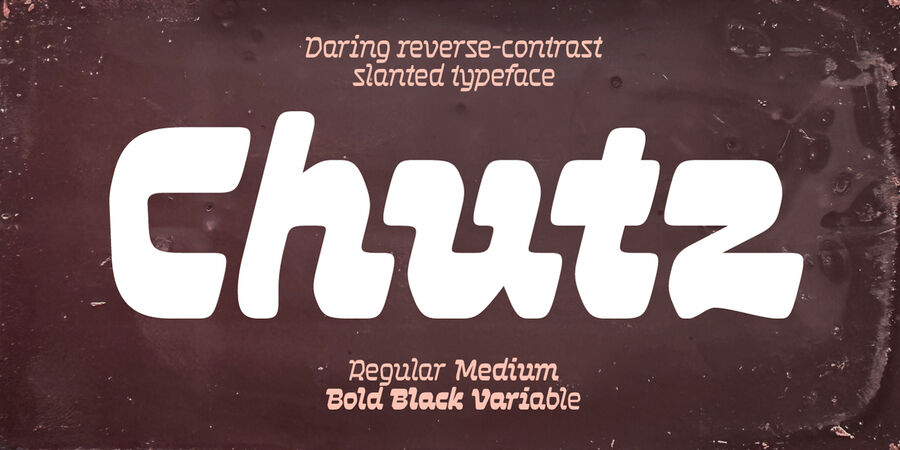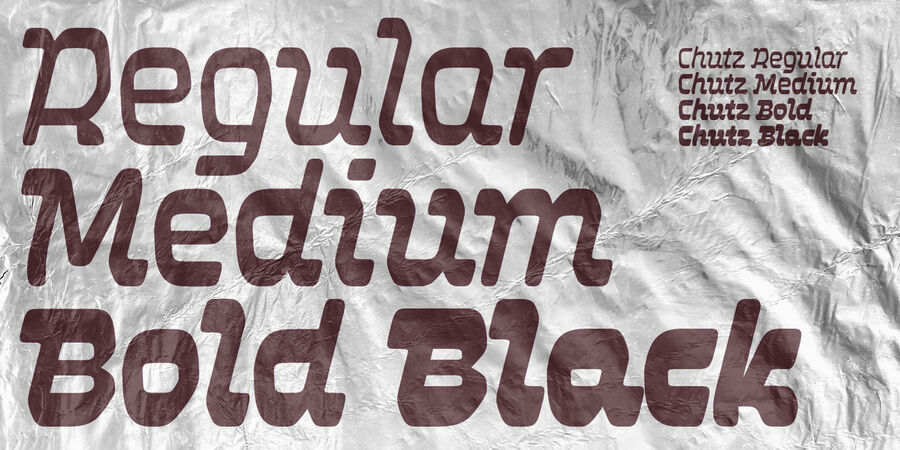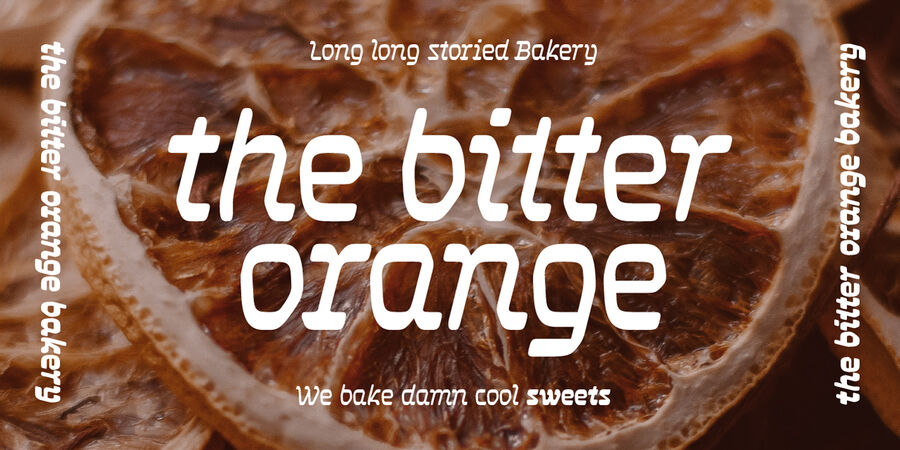
Опис гарнітури ChutzChutz це зухвала шрифтова гарнітура з нахилом, зворотним контрастом та горизонтально спрямованими штрихами, розроблена для єврейського бренду Chutzpah компанії Feisty Foods розташованої в Брукліні, Нью-Йорк. Шрифт має три мети – відчуватись єврейським, смачним, та зухвалим. Для передачі характеру івриту в латинській, грецькій та кириличній писемності застосовані такі засоби як реверсний контраст (протилежний латинському) де горизонтальні штрихи товщі за вертикальні, та горизонтально спрямовані каліграфічні штрихи притаманні івритській писемності і які роблять літери більш квадратними.
Щоб виглядати смачно та відчуватись як тісто (у стилях Bold і Black) дизайн отримав м'які заокруглені деталі та насичений типографічний колір. Для передачі сміливості та зухвалості структура літер отримала нахил різного куту для різних літер. Наприклад більшість літер мають латинський нахил (направо), а деякі інші літери як то CGOQabcdegopqy мають притаманний івриту нахил (наліво). Таке поєднання різних кутів нахилу надає шрифту зухвалий комплексний характер готовий до сміливих дій. Стилі: Regular, Medium, Bold, Black, Variable Font. У промо зображеннях використані фото Ольги Рафайлик, та фото Marta Dzedyshko, Josh Sorenson з Pexels. Шрифт розробив Михайло Рафайлик у 2023 році та значно розширені та оновлені у 2024. Chutz підтримує 111 мовУкраїнська, Англійська, Німецька, Польська, Португальська, Іспанська, Грузинська, Казахська, Іврит, Французька, Грецька (сучасна), Арабська, В'єтнамська, Російська, Чеська, Голландська, Італійська, Шведська, Турецька, Фінська, Білоруська, Грецька, Татарська, Сербська, Болгарська, Естонська, Литовська, Албанська, Африкаанс, Баскська, Бретонська, Валенсаска, Galician, Гельська (Шотландська), Данська, Індонезійська, Ірландська, Ісландська (Win), Каракалпацька, Каталонська, Норвезька, Окситанська, Ретороманська, Самі Лулі, Тсванська, Узбецька (Лат.), Фарерська, фризька, Чаморро, Естонська (Win), Південносаамська, Албанська (Win), Угорська, Верхньолужицька, Карельська, Латвійська (Mac), Литовська (Mac), Маорійські (Mac), Молдавська (Лат.), Нижньолужицька, Румунська (Win), Словацька, Словенська, Туркменська (Лат.), Хорватська (Win), Естонська (Mac), Курдська, Латишська, Маорійські, Руминська, Абазинська, Аварська, Агульська, Адигейська, Даргинську, Інгуську, Кабардино-Черкеська, Кабардинська, Карачаєво-Балкарська, Кумицька, Лакська, Лезгинська, Македонську, Мордовсько-Мокшанська, Мордовсько-Ерзянська, Ногайська, Рутульська, Табасаранська, Татська, Цахурська, Чеченська, Азербайджанська (Кир.), Башкирська, Бурятська, Дунганска, Коломацька, Киргизька, Монгольська (Кир.), Таджицька, Талиська, Тувинська, Туркменська (Кир.), Узбецька (Кир.), Уйгурська, Ідиш, Татська (Єврейська), Дарі, Малайська, Перська (Фарсі), Пуштунська, Урду Функції сімейства шрифтів ChutzЗастосування гарнітури у верстці:
Асоціації з сімейством шрифтів ChutzОсобистість і характер гарнітури:
М'який, доброзичливий, добрий, оптимістичний, літній, смачний, здоровий, свіжий, оригінальний, самобутній, цікавий, пластичний, гнучкий, гладенький, якісний, грайливий, динамічний, теплий, святковий, апетитний, емоційний, яскравий, спекотний, кольоровий, експериментальний, тусовочний, сміливий, південний, непосидючий, рухливий, активний, прикольний, молодіжний, характерний, виразний, міський, дивний, живий, дозвільний, двіжняковий, ритмічний, студентськиий, екзотичний, спекотливий, потішний, рукотворний, веселий, помітний, тісний, мультяшний, гарячий, тропічний, дитячий, радісний, артистичний, вуличний, творчий, помірний, симпатичний, мотивуючий, сильний, привітний, позитивний, ручний, важкий, товстий, щедрий, рясний, насичений, смішний, добродушний, стиглий, соковитий, милий, пишний, сімейний, няшний, усміхнений, солодкий, щасливий, фруктовий, ягідний